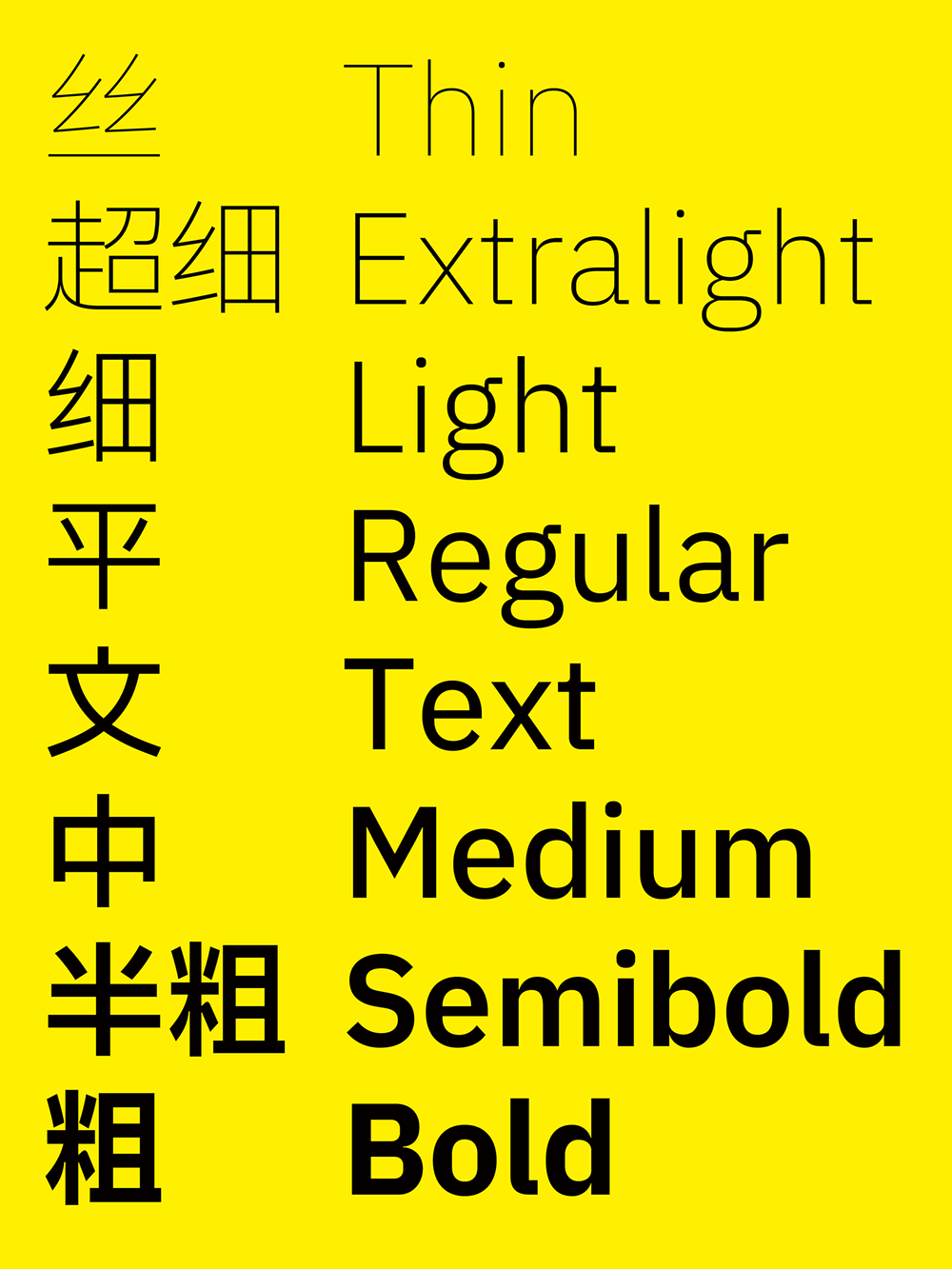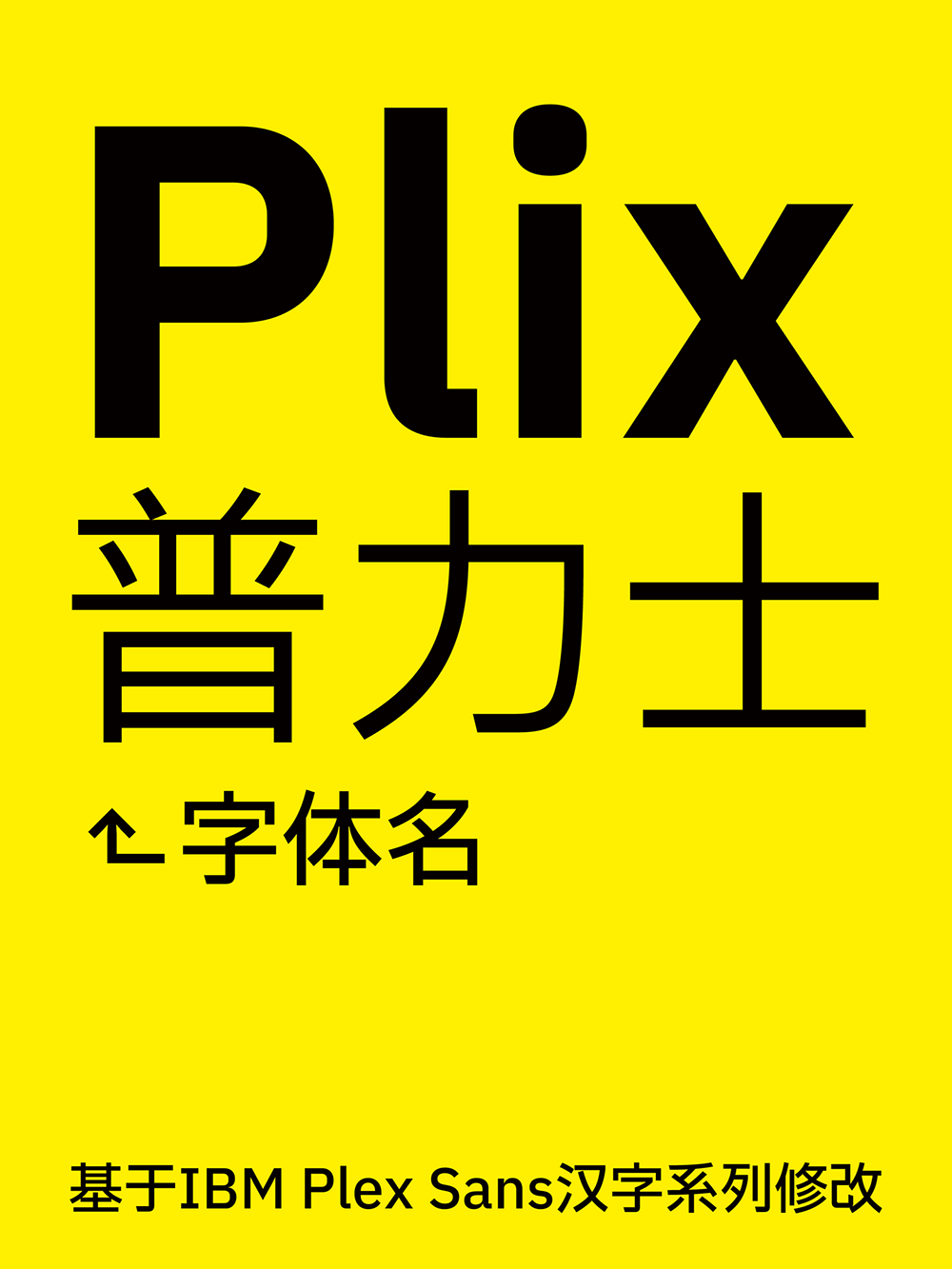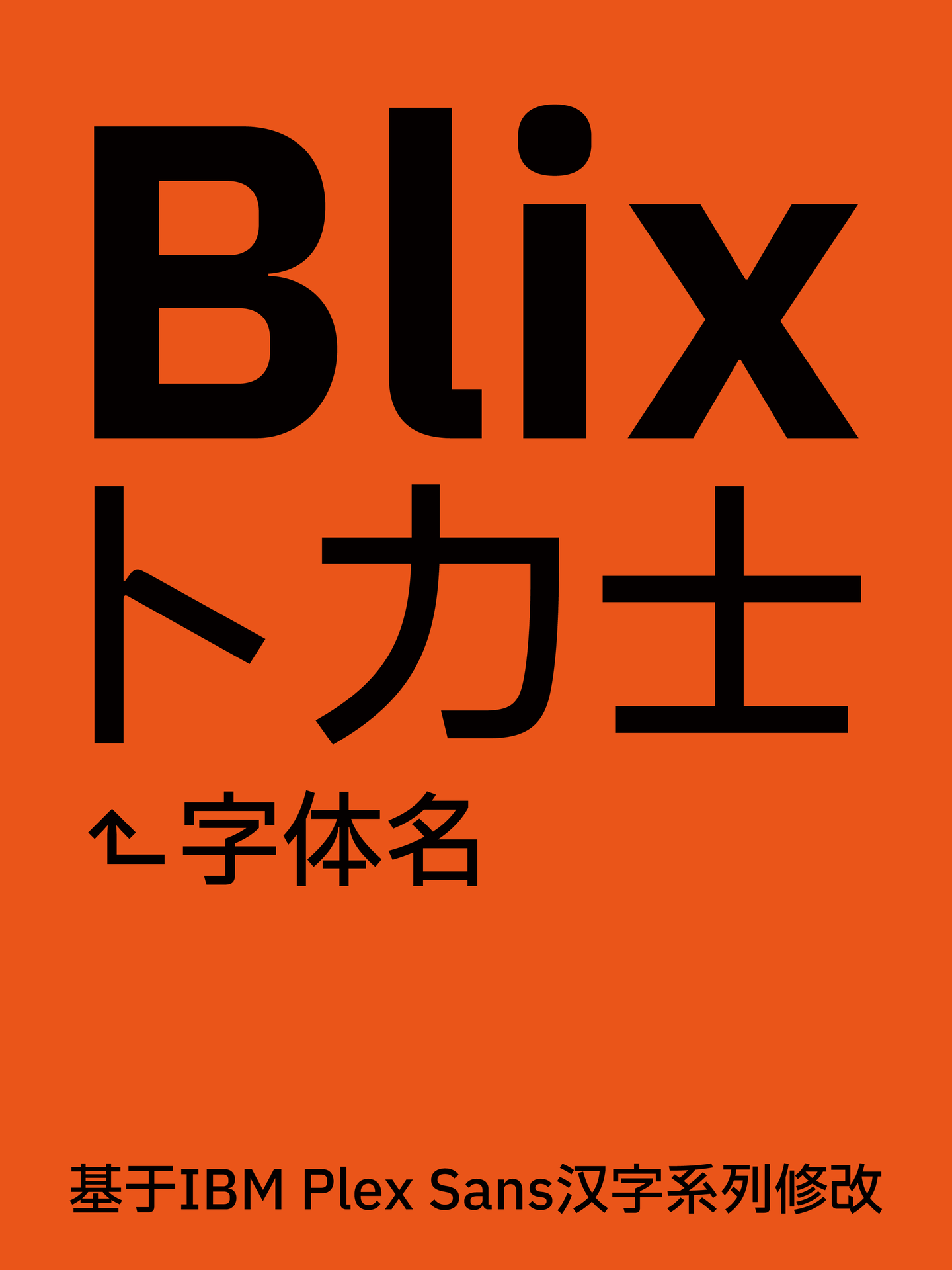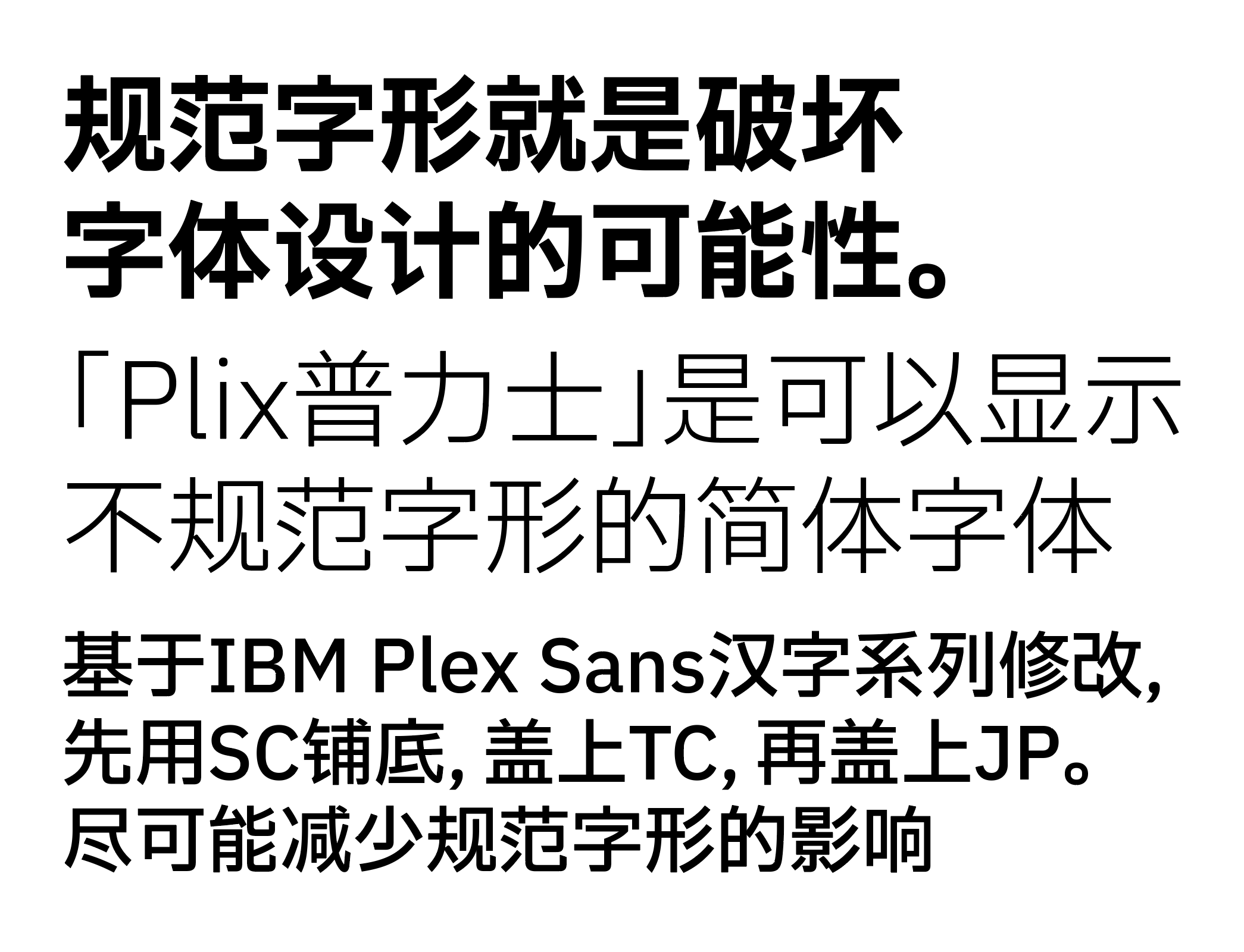
Plix普力士字体:基于IBM Plex Sans汉字系列修改合并的免费商用字体
Plix普力士字体是一款基于IBM Plex Sans汉字系列进行修改的合并字体,它不仅支持简体字的显示,还能展示一些不规范字形的简体字。根据标点符号的居中和居角可以分为两种:
• Plix普力士:用JP补上TC,再补上SC,标点居角,日本字形。
• Blix卜力士:用TC补上JP,再补上SC,标点居中,繁中字形。
设计上,Plix普力士字体继承了IBM Plex系列的风格,曲中带直,90°直角的转折和交叉处的ink trap,既有复古的人潮流感又有现代的机械感,在科幻、电子、潮流艺术等场景中尤为适用。